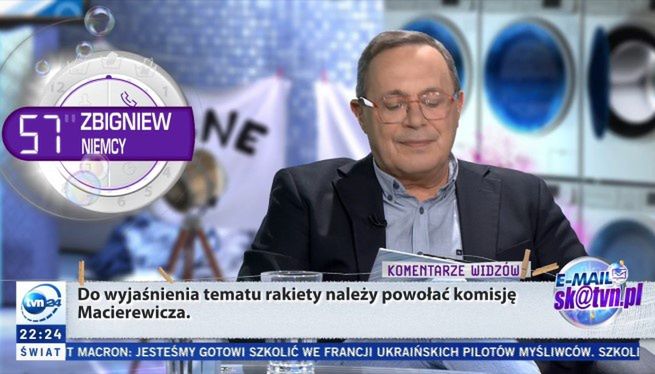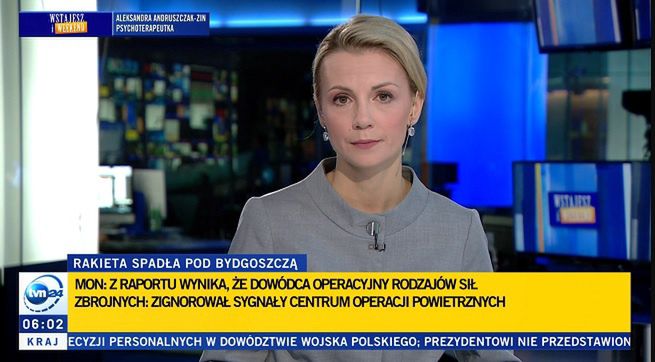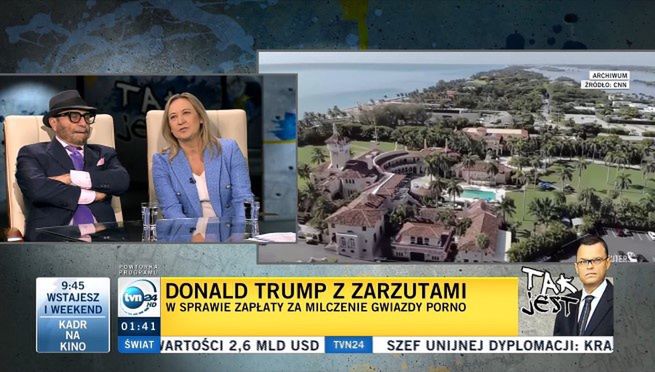
Część widzów krytykuje nową oprawę TVN24. „Jak dla niedowidzących”
Po 14 latach TVN24 zmienił oprawę antenową. - Nie zauroczyła mnie, ale mam pozytywne skojarzenia – ocenia Marek Czyż, szef informacji Radia ZET.  Pojawiły się jednak krytyczne komentarze widzów. Twierdzą, że belki zajmują zbyt dużo miejsca na ekranie, a logo i zegar są zbyt duże.
Do poprzednich zmian w oprawie graficznej TVN24 doszło w 2009 roku, kiedy stacja przechodziła z formatu 4:3 na 16:9. Od soboty dolna belka i pasek z informacjami zostały wydłużone. W związku z tym lewego dolnego rogu zniknął ticker, w którym znajdują się informacje o kolejnych pozycjach programowych w TVN24. Umieszczono go teraz w górnym lewym rogu i wygląda zupełnie inaczej - jest podłużny. Po weekendzie stacja zrezygnowała jednak z pokazywania nowego tickera, nie wiadomo czy on powróci.
Oprawa dalej utrzymana jest w kolorach białym i niebieskim, przy informacjach pilnych pojawia się - tak jak dotąd - belka w kolorze żółtym. Żółty kolor pojawia się tez w tle napisu „na żywo”.
Nową czołówkę otrzymało pasmo „Dzień na żywo”, nadawane w dni powszednie o 10, a w soboty o 11. Bez zmian pozostała grafika używana np. w zapowiedziach programów.
Sam TVN Warner Bros. Discovery nie komentuje szerzej zmian, nie ogłaszał ich także wcześniej. - Trochę odświeżamy. Nic więcej się nie zmienia, na razie nic więcej nie będzie się działo – usłyszeliśmy w biurze prasowym firmy.
Widzowie liczyli na minimalizm
Z logotypu TVN24 zniknęły litery HD. To naturalna zmiana, bo dzisiaj większość stacji telewizyjnych jest nadawanych w wysokiej rozdzielczości. Choć część widzów TVN24 w mediach społecznościowych i na forach dyskusyjnych zmiany uznała za pozytywne, inni krytykowali stację. - Zamiast mniejsze, minimalistyczne, to jest to co było - tylko by mocniej biło po oczach i jeszcze bardziej wypalało ekrany. I te straszliwe zapowiedzi latające 24/h u góry, która mają jedno zadanie - przeszkadzać. Jak w jakiejś telewizji osiedlowej. Po co tyle śmieci na ekranie? Chyba każdy słyszy o czym mowa. Ale nie, musi mieć jeszcze potwierdzenie na pięciu belkach jednocześnie. I żeby one pojawiały się co jakiś czas przy ważnej informacji, to nie co zdanie, wątek - nowa olbrzymia belka. Obłęd – napisał pod artykułem na Wirtualnemedia.pl jeden z internautów.
Kilka miesięcy temu informowaliśmy, że intensywne kolory w logotypach stacji i paski kanałów informacyjnych mogą prowadzić do „wypalenia” matryc telewizorów OLED. - Zjawisko retencji, czyli właśnie wypalania matrycy poprzez długotrwałe wyświetlanie jednego statycznego elementu na ekranie (np. logo stacji telewizyjnej czy paska nawigacji w grach) występuje w przypadku telewizorów OLED. Wynika to po prostu z konstrukcji samej matrycy z diodami organicznymi i jest efektem nadmiernej eksploatacji sprzętu. Problem wypalenia może pojawić się przy codziennym naprawdę wielogodzinnym korzystaniu z telewizora w tym samym widoku, gdzie na ekranie nieprzerwanie wyświetlany jest jeden niezmienny element, np. logotyp lub pasek z newsami kanału informacyjnego. Właśnie dlatego producenci telewizorów przestrzegają przed takim sposobem korzystania z tych urządzeń - wyjaśniał w rozmowie z Wirtualnemedia.pl Michał Szczerowoda, product manager TV, TP Vision Europe, właściciela marki Philips.
Widzowie od dawna apelują do nadawców i Krajowej Rady Radiofonii i Telewizji o wprowadzenie półprzeźroczystych logotypów. Regulator twierdzi, że nie może ingerować w politykę poszczególnych stacji. - Kwestie intensywności natężenia koloru logo stacji, kategorii wiekowej, jak i innych elementów oprawy graficznej programu, nie podlegają kompetencjom KRRiT. Zgodnie z art. 13 ust. 1 ustawy o radiofonii i telewizji nadawca kształtuje program samodzielnie (…) i odpowiada za jego treść – poinformowała internautów KRRiT.
Ułatwienie dla starszych widzów?
Krytyka wobec TVN24 dotyczy też dużego zegara towarzyszącego logotypowi. - Wielkie „coś” zajmujące, 1/3 ekranu, wyglądające, jak robione w Paincie 15 minut przed startem programu + wielki napis K R A J / Ś W I A T. Nie pasujący do niczego zegar, który wygląda jakby był przystosowany dla osób niedowidzących – ocenił jeden z użytkowników „Forum SAT Kuriera”.  Inny internauta bronił stacji. - Nie mierzyłbym swoją miarą. Poczekaj spokojnie do 50-tki. Ocenisz sam czy jesteś dowidzący czy niedowidzący. Mała czcionka, belka na mniejszych ekranach bez okularów dla wielu osób jest nieczytelna - zauważył.
Przed rokiem podawaliśmy dane o strukturze widzów TVN24. Wynika z nich, że 63 proc. odbiorców kanału stanowi grupa wiekowa 65+. Podobnie wygląda widownia TVP Info i Polsat News. Kanały informacyjne biorą więc pod uwagę demografię i starają się, żeby ich przekaz był jak najbardziej czytelny i słyszalny dla widzów. W przypadku niewielkiej czcionki mogą oni po prostu wybrać inną stację.
Pootwierane drzwi
Zdaniem ekspertów modyfikacja nie jest niczym rewolucyjnym, choć nic jej nie dolega. - Nie zauroczyła mnie, ale mam pozytywne skojarzenia – przyznaje Marek Czyż, dyrektor informacji Radia ZET, w przeszłości m.in. dyrektor programowy TVS, prowadzący liczne programy informacyjne i publicystyczne w TVP Info, TVP3 Katowice i Superstacji. - W obszarze opraw wizualnych telewizji są same pootwierane drzwi, więc nie da się żadnych wyważyć i zbudować czegoś szokującego. One muszą spełniać jeden warunek, mieć jeden walor: być przejrzyste, komunikatywne. I takie w TVN24 są – zaznacza.
- Ta oprawa nie jest agresywna, nie ma tam trąb i bębnów, to jest dynamiczne, ale łagodne, przejrzyste i czytelne. Komunikaty są wystarczająco odseparowane od siebie, by dobrze wyglądały. Oczywiście wszystko błękitno-niebiesko-szare, bo telewizja na świecie używa takich barw – dodaje Czyż.
- To drobna korekta – wtóruje mu dr hab. Adam Szynol, medioznawca z Uniwersytetu Wrocławskiego. - Nie jest to transformacja, nawet sam nadawca nie chce się specjalnie chwalić. Gdyby to była duża zmiana, na pewno przygotowano by odpowiednią konferencję, marketingowy szum wokół. Widzimy zatem, że ta zmiana ma charakter drobnej korekty, kosmetyki, można by powiedzieć, że wręcz faceliftingu. To odświeżenie, lekka zmiana – dodaje.